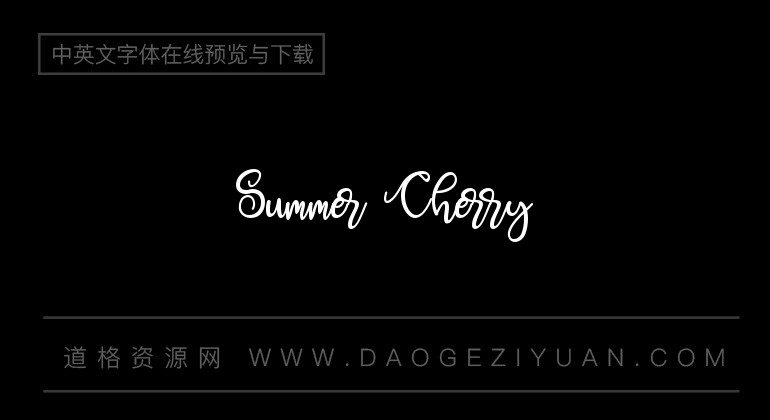
Summer Cherry
Summer Cherry 是一款由 Kimmy Lee 设计的手写风格字体,适用于各种设计项目,如印刷品设计、海报、包装、品牌标识等。这款字体的特点是笔画流畅自然,线条轻盈优美,字体整体感觉温暖柔和,适合用于传达友善、轻松和愉悦的氛围。Summer Cherry 字体包括常规、粗体和斜体三种字重,同时还包括了英文字母、数字和标点符号,支持多种语言,非常适合用于设计师和排版师的工作。
Summer Cherry是一款非常不错的手写艺术字体,具有很好的视觉感,适合于文化类的宣传设计、商业类品牌的广告和产品包装设计以及个性化文字排版等较多场景。